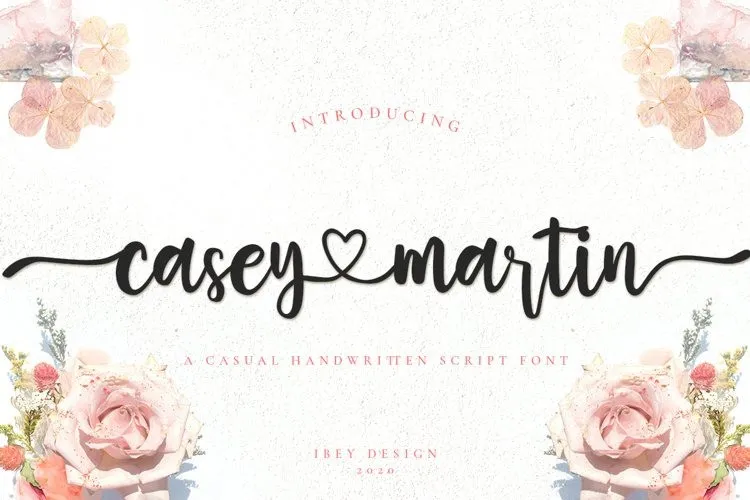
Esta fonte é uma moderna adição à coleção dos fonts de escritura manual que oferece um estilo encantador com conexões no meio do coração. Desenhada para apresentar um luxo sofisticado, este font traz alto detalhamento a cada letra. Ideal para designers em busca de gráficos exuberantes e elegantes, esta font ‘Casey Martin’ é perfeita tanto para editoriais quanto para trabalhos digitais que exigem estilo único e profissionalismo. Se você está procurando por uma fonte que combine modernidade com um toque refinado, a Casey Martin oferece o ideal combinado de beleza visual e detalhe meticuloso.